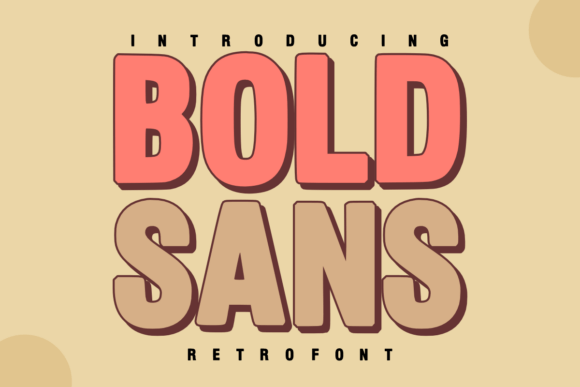
Bold Sans
Revenez au Temps des Classiques
Le font Bold Sans est une merveilleuse combinaison de charme vintage et de modernité audacieuse. Avec sa structure épaisse et chunky, ainsi qu'une ombre de 3D lisse, il apporte un instant de nostalgie à tout designer. Inspiré par l'esthétique "groeux retro", il est conçu pour faire ressortir vos titres et "éclater" d'énergie.
Caractéristiques du Font Bold Sans
- Structure épaisse et chunky : un style vintage authentique qui évoque les années 60 et 70
- Ombre 3D lisse : un effet moderne qui donne une profondeur aux titres
- Ajustable à tout type de design : streetwear, affiches retro, branding quirky, etc.
- Performant et épuré : un font idéal pour les designers qui cherchent un équilibre parfait entre modernité et charme vintage
Intégrez Bold Sans dans votre Création
Bienvenue dans le monde de Bold Sans ! Ce font est parfait pour les designers qui cherchent à créer un design unique et énergique. Avec ses caractéristiques uniques et sa flexibilité, il est idéal pour les projets variés, du streetwear au branding. Commencez à utiliser Bold Sans aujourd'hui et découvrez comment il peut apporter un élément de personnalité à vos créations.